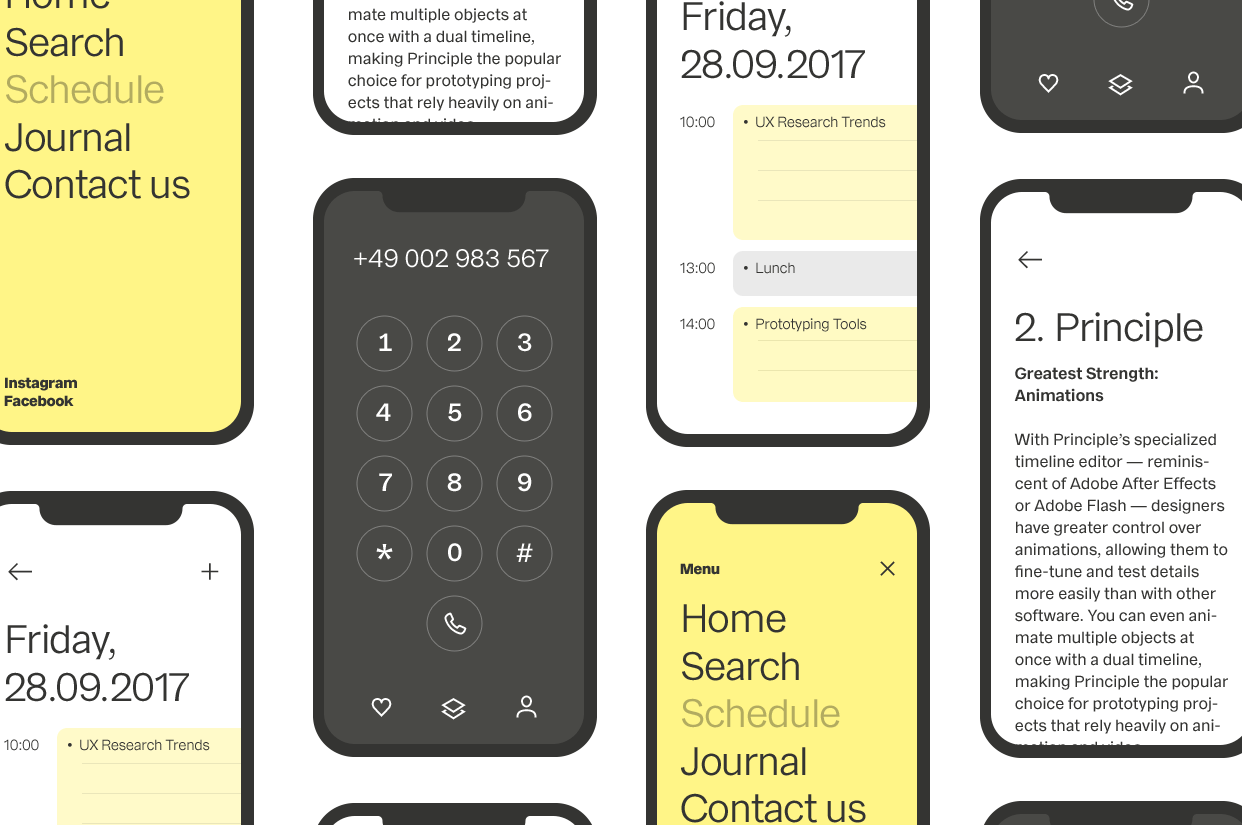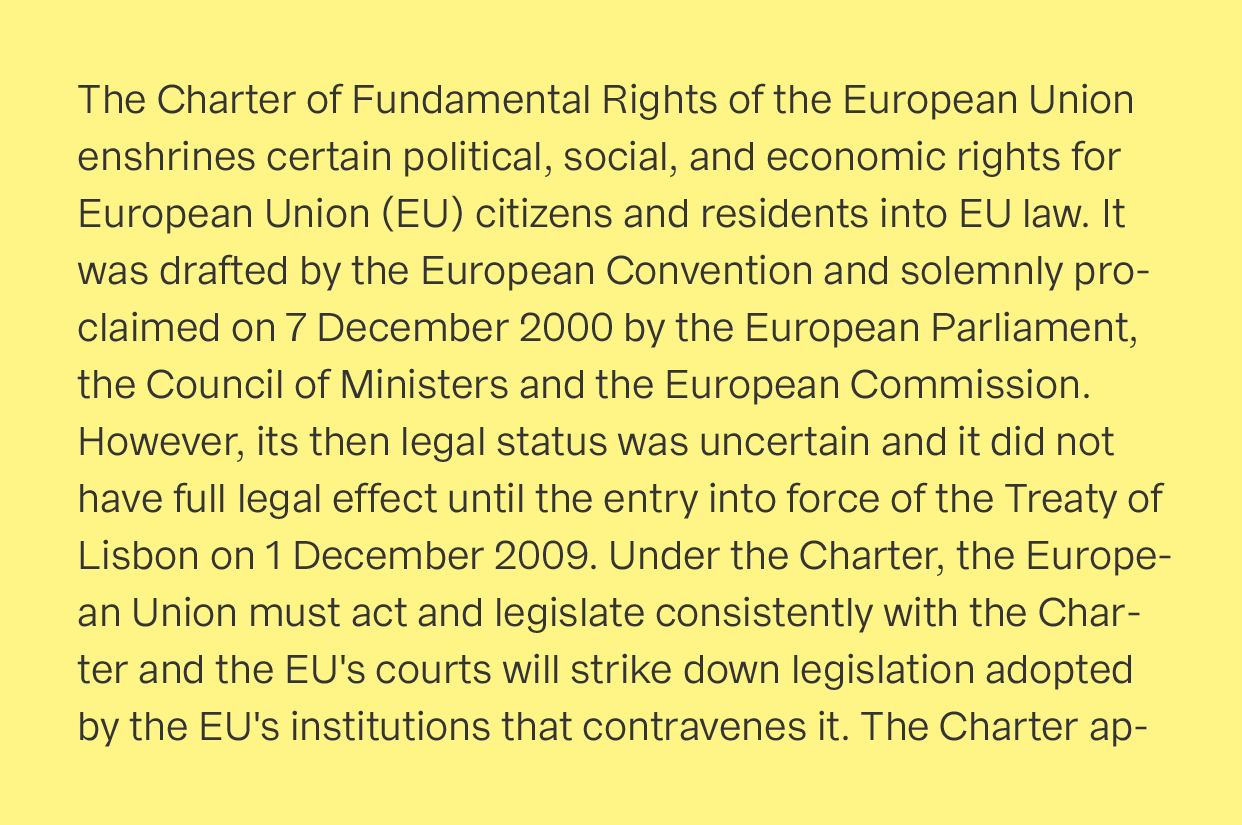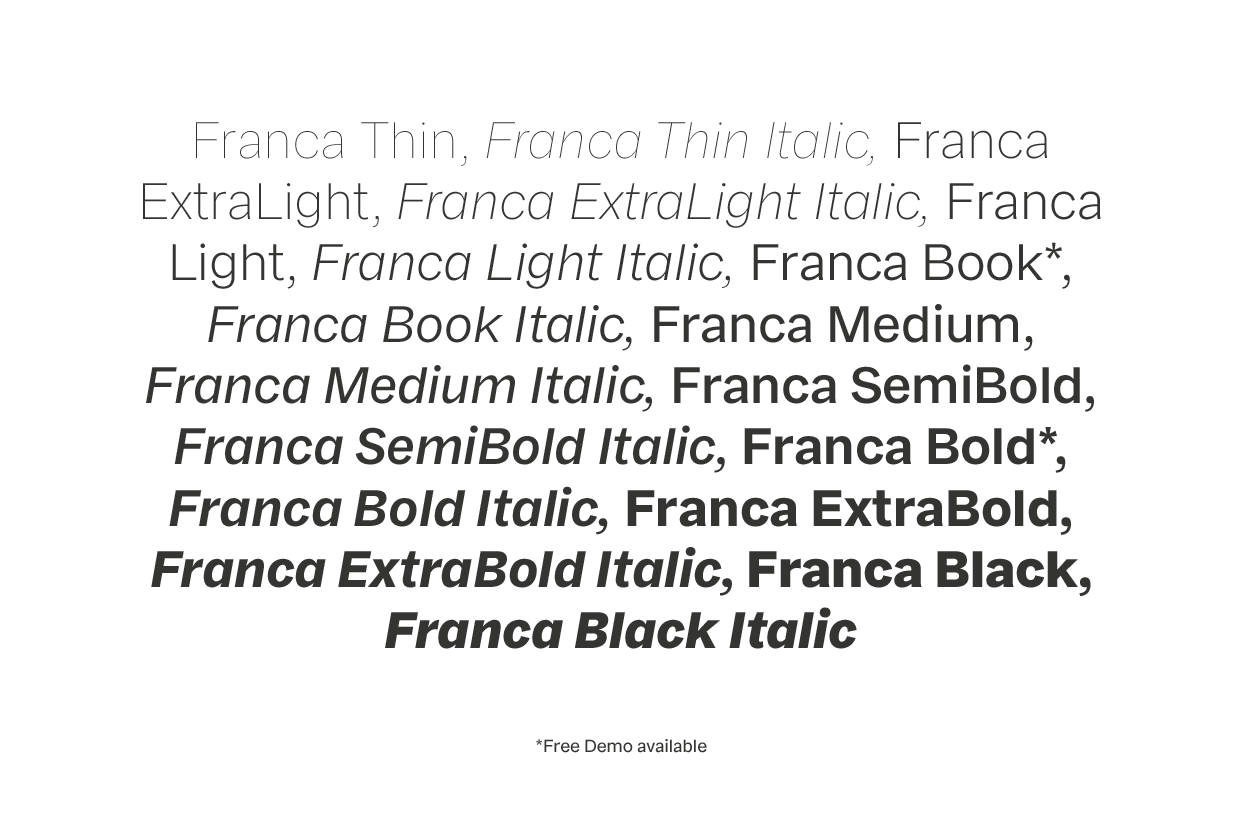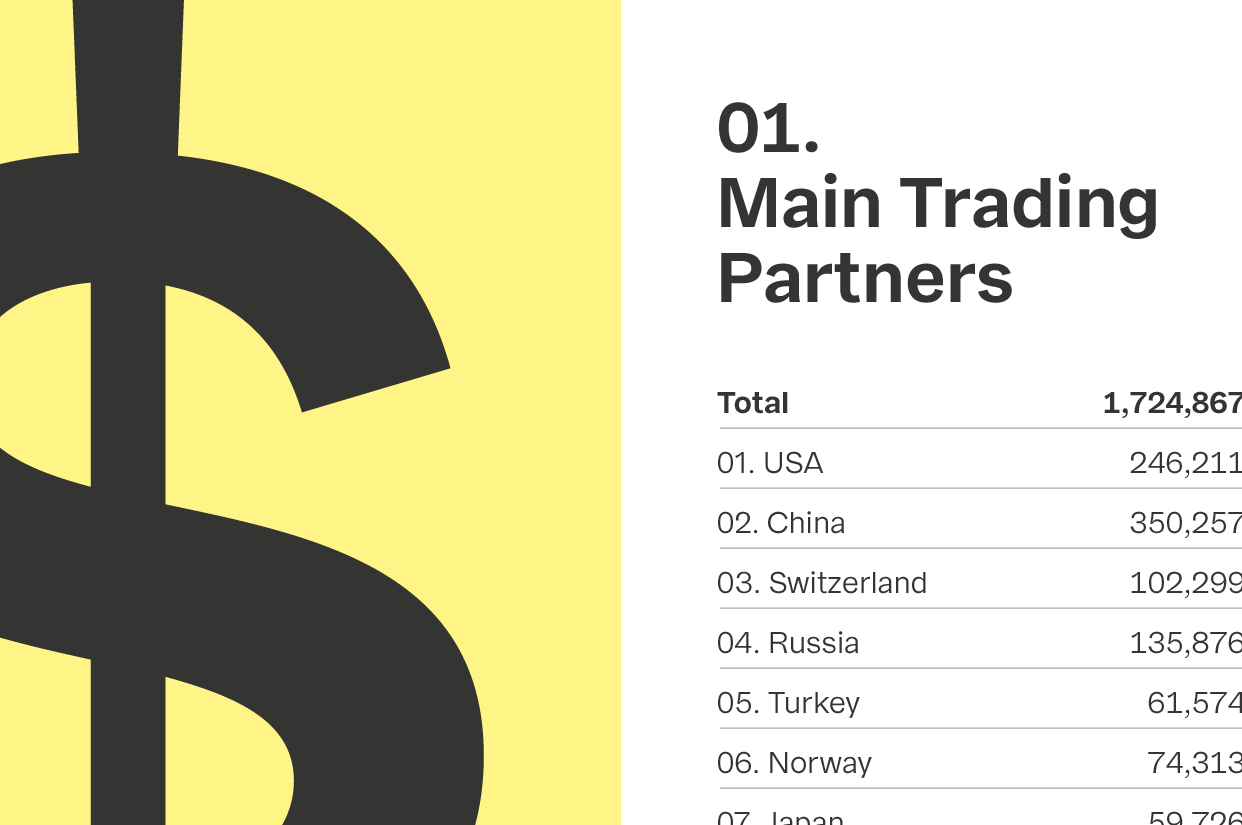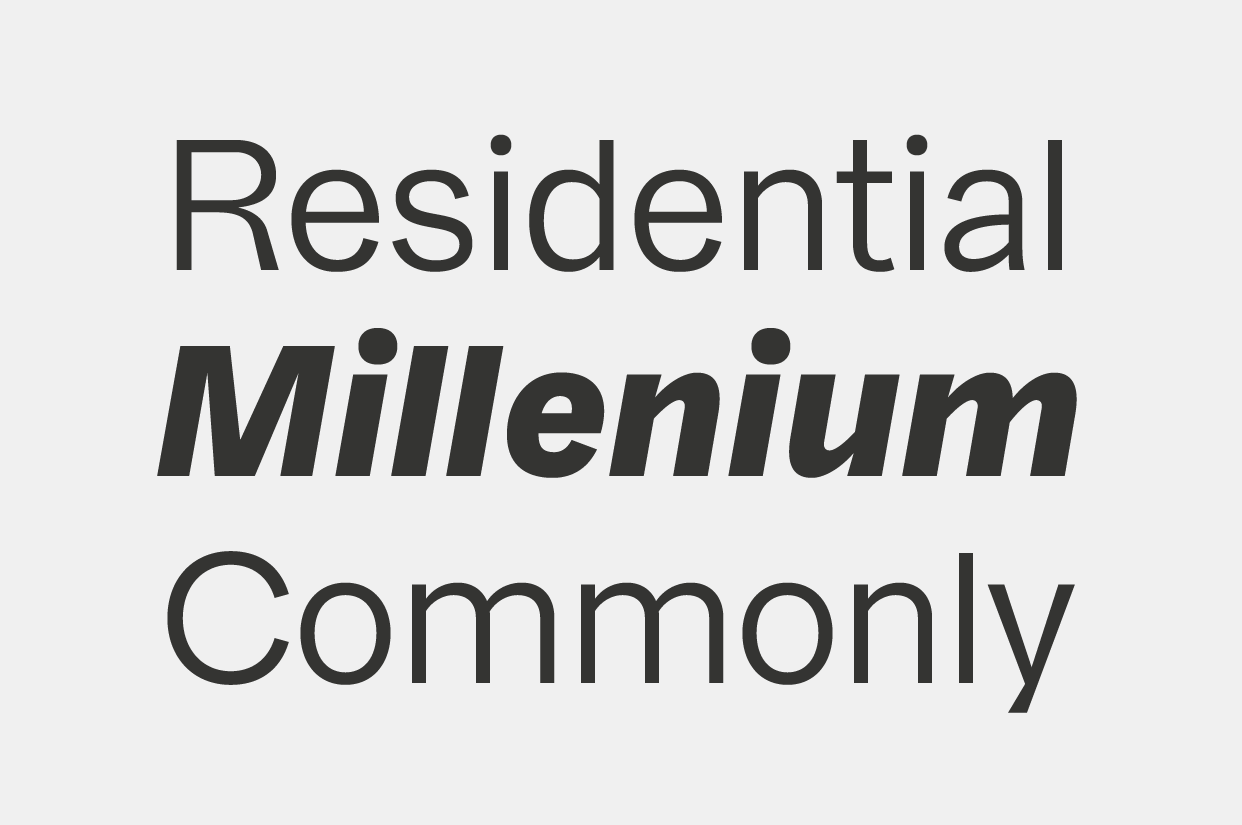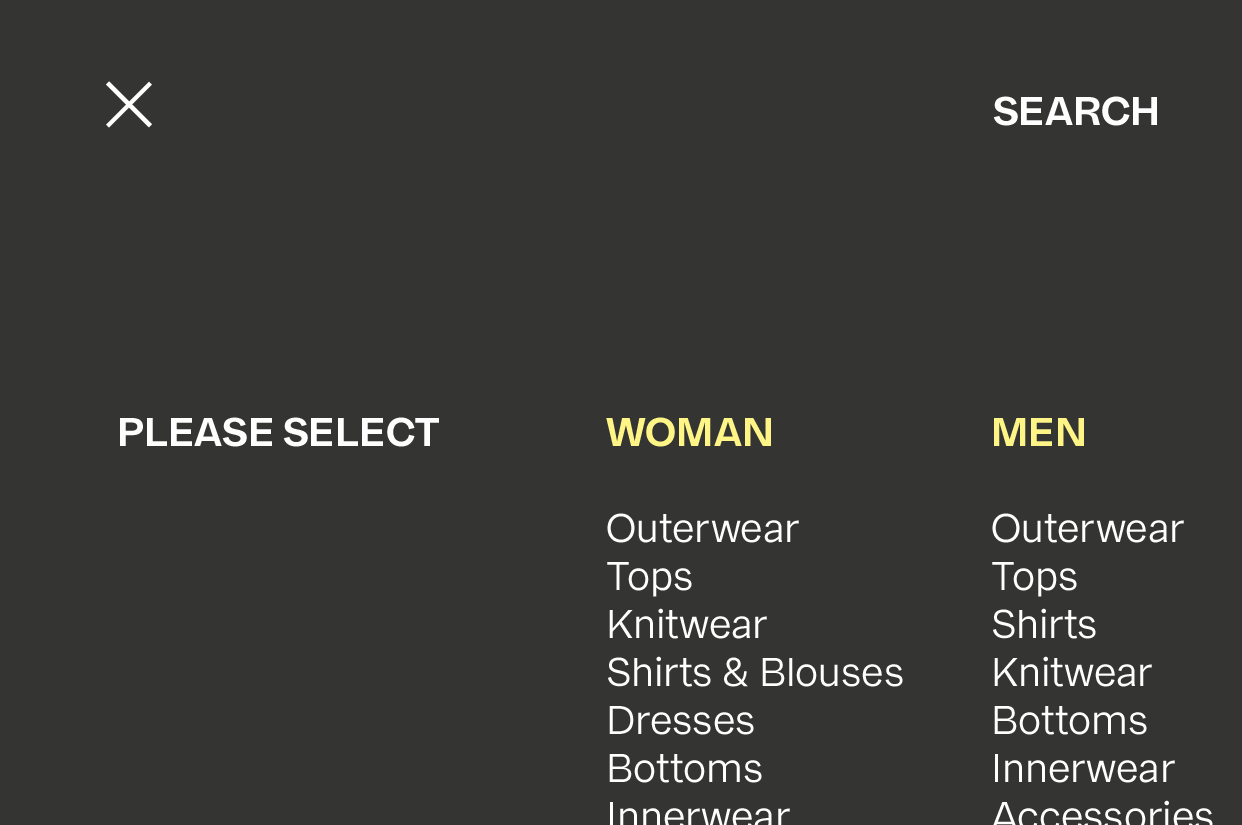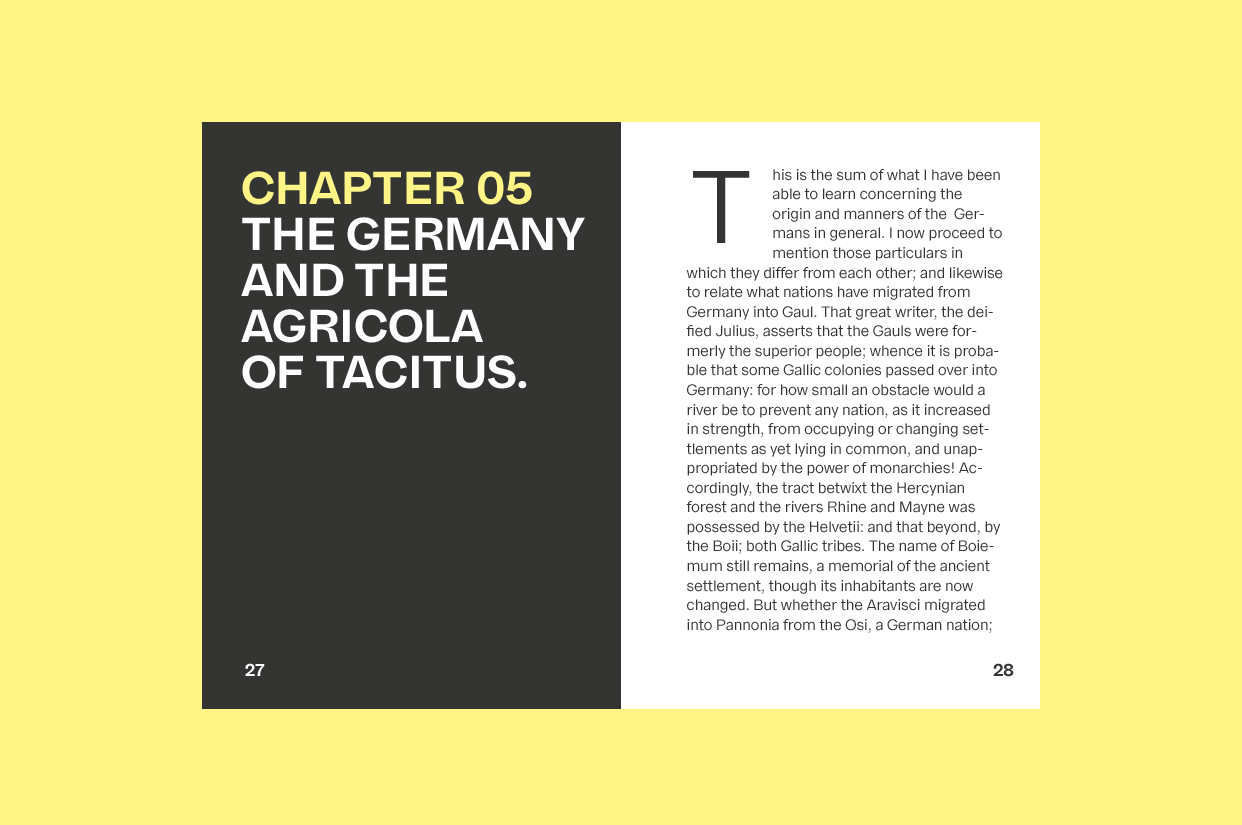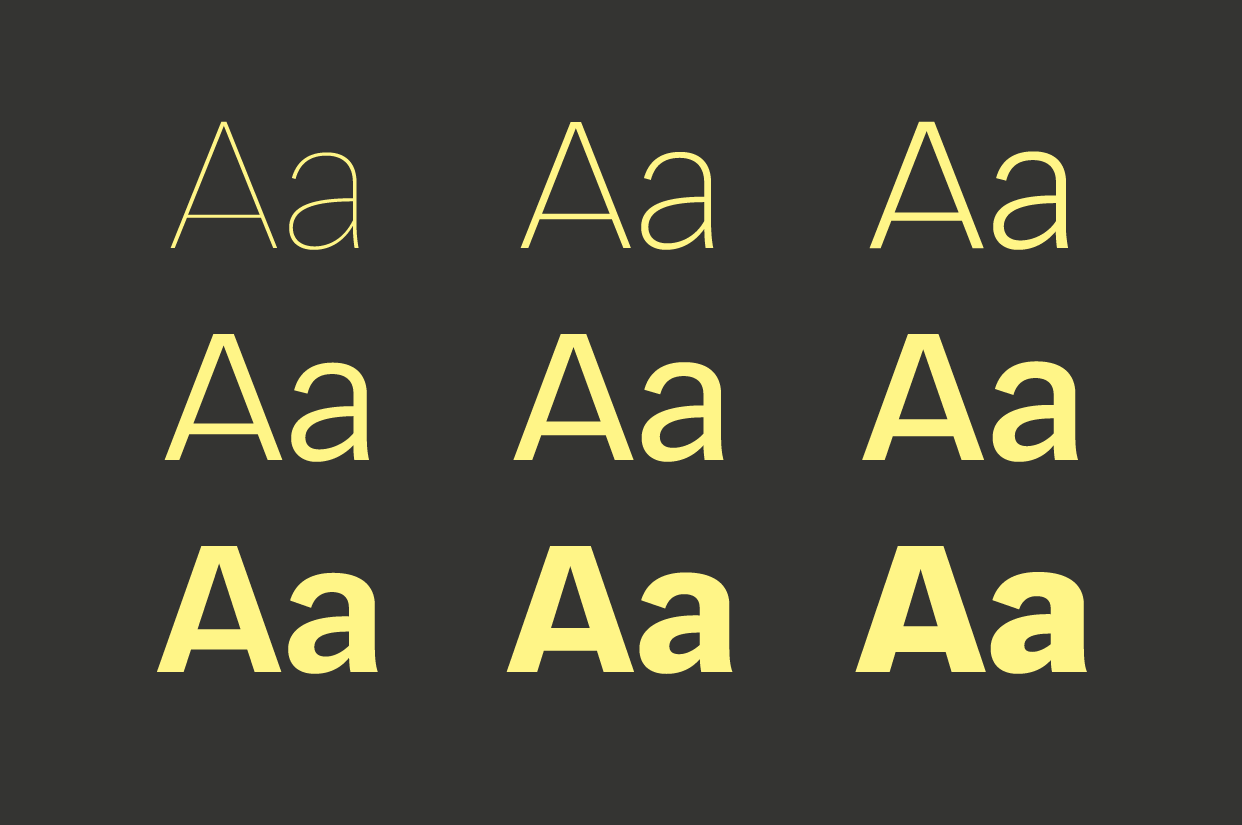
Franca,Francafontfamily展示了18种风格的浪漫怪诞家庭,Francafontfamily,Francafontfamily。Francafontfamily怪诞家庭在新的八大数字中。他们的灵感来自于对经典怪诞模式“中性”字体的全新解读。这些中性字体在研究期间用于示范性的ELVECTICA、University或Normal Protesk,此外,还对黑格尔的美国代表给予了额外的关注。因此,这导致了重新解释的初始阶段。这是在名称中反映出来的,并与每个人(弗兰克兰)和赫尔维蒂(加利福尼亚)的通用字体的名称混合在一起。